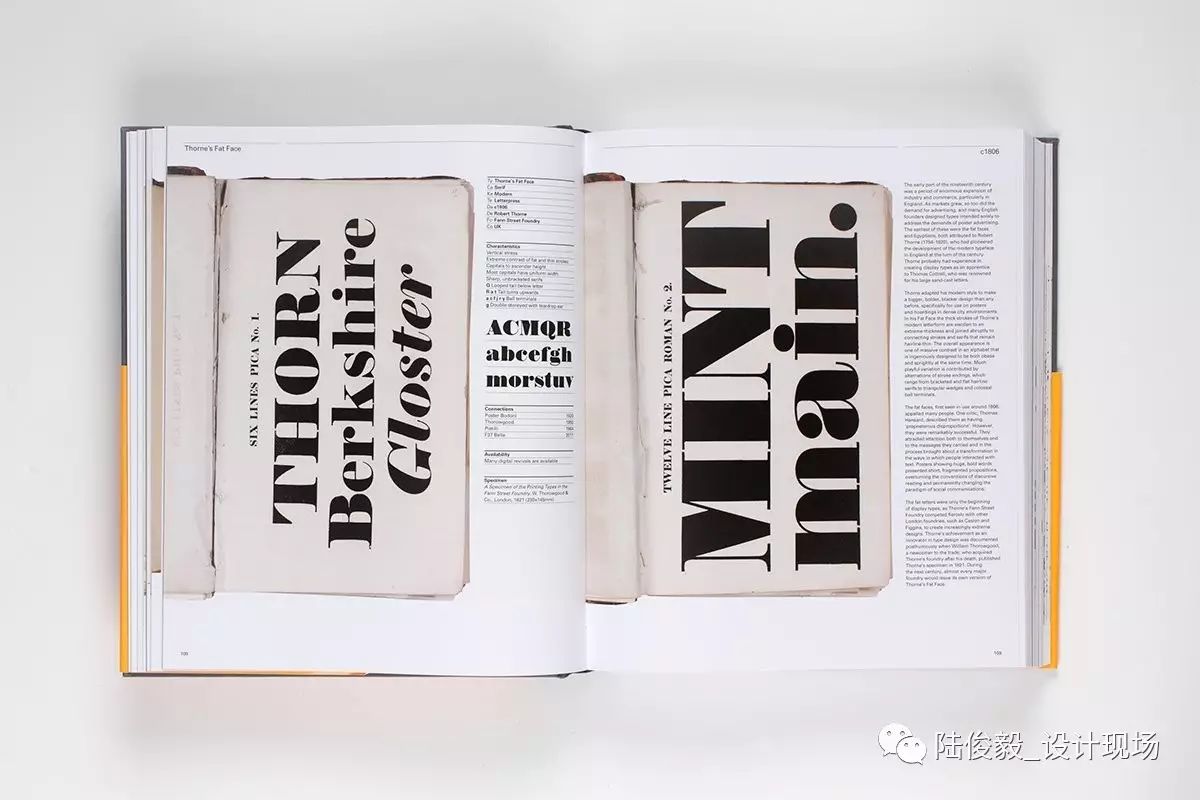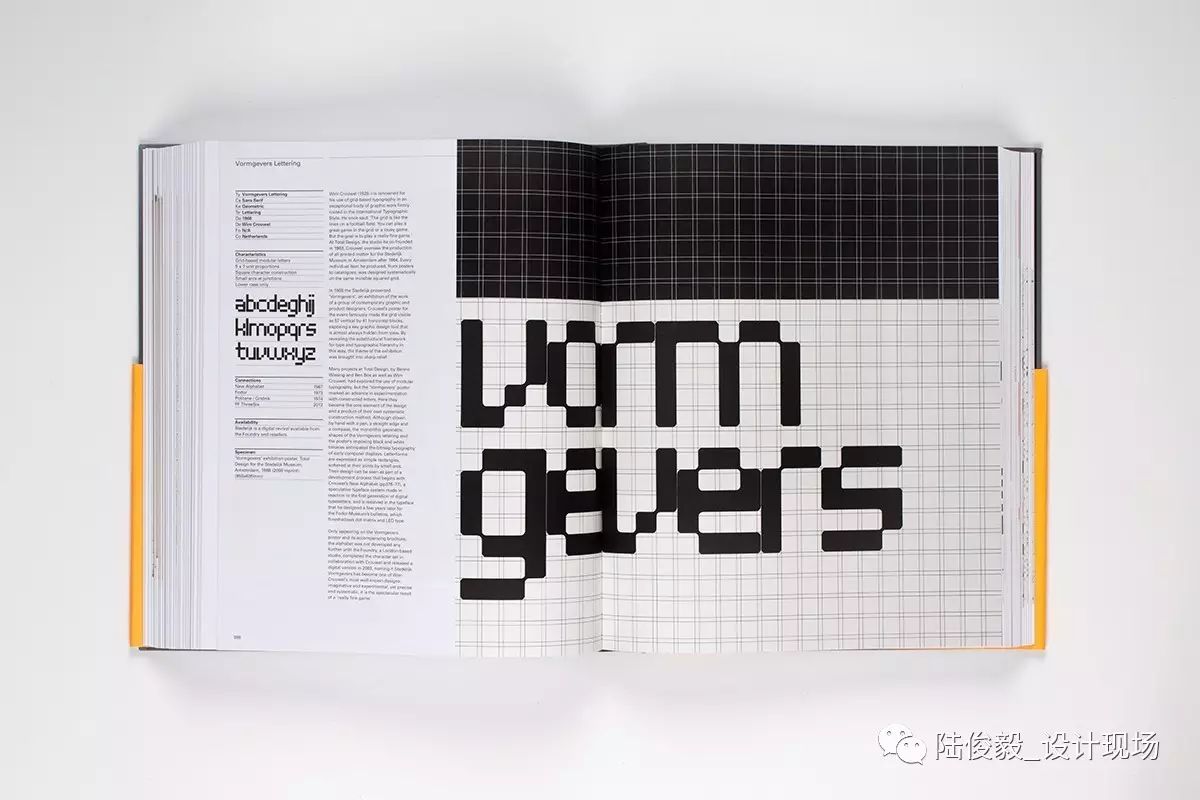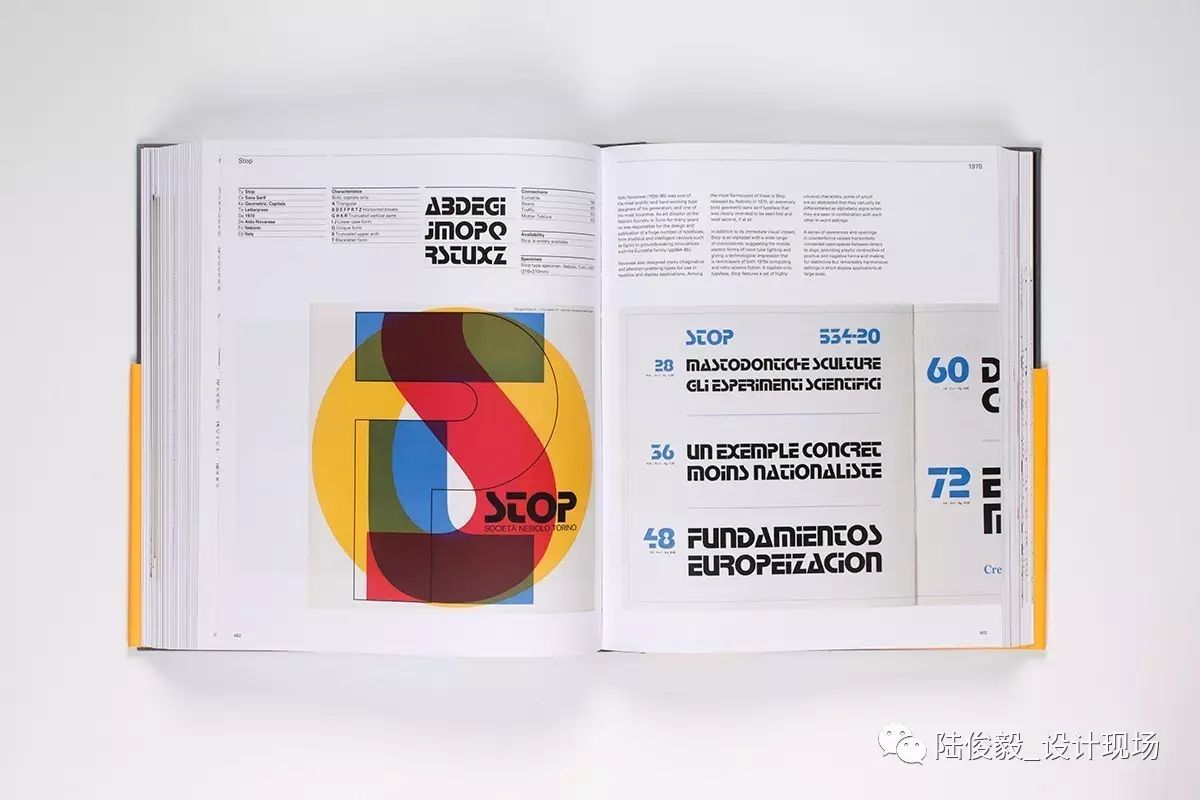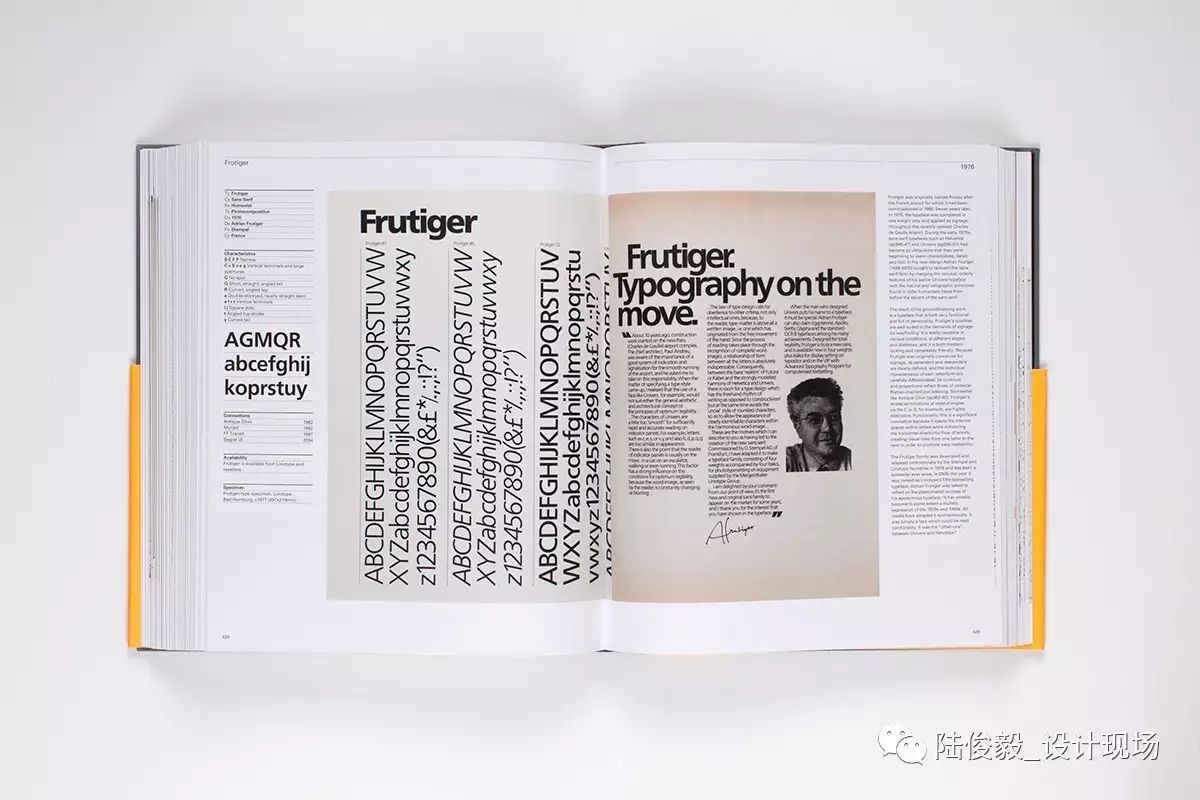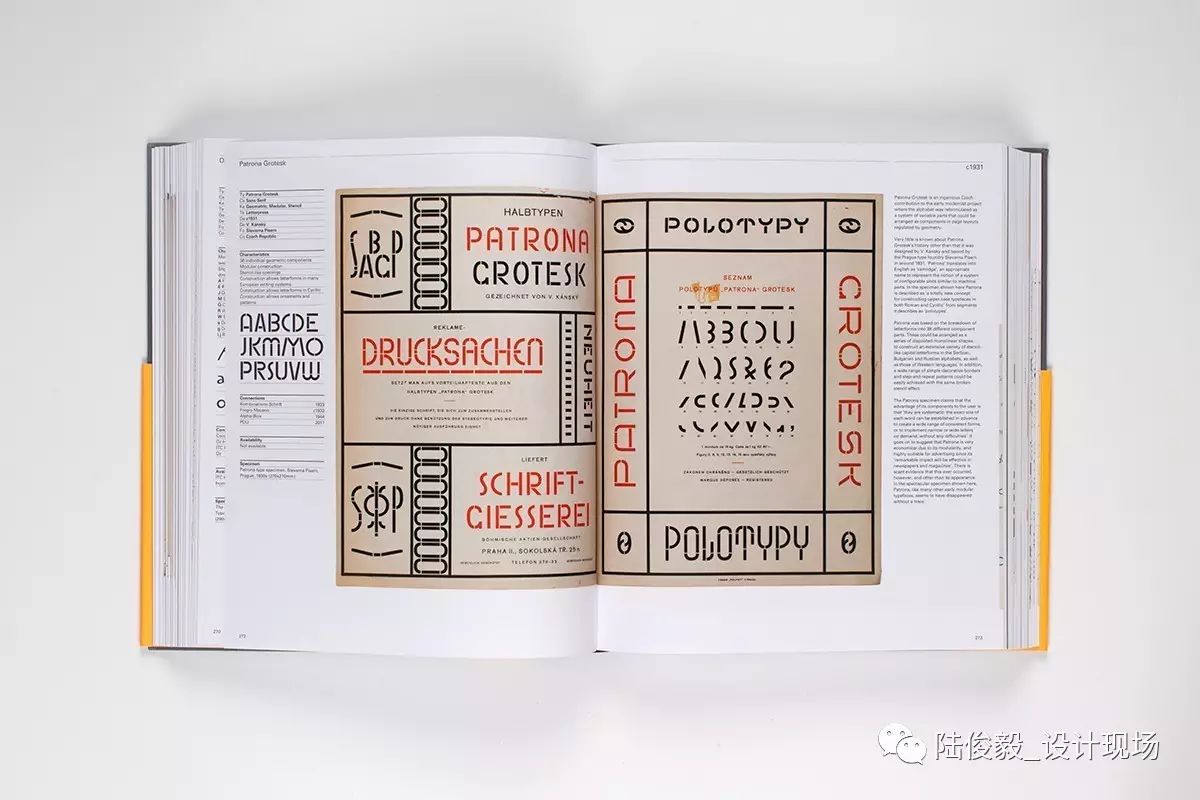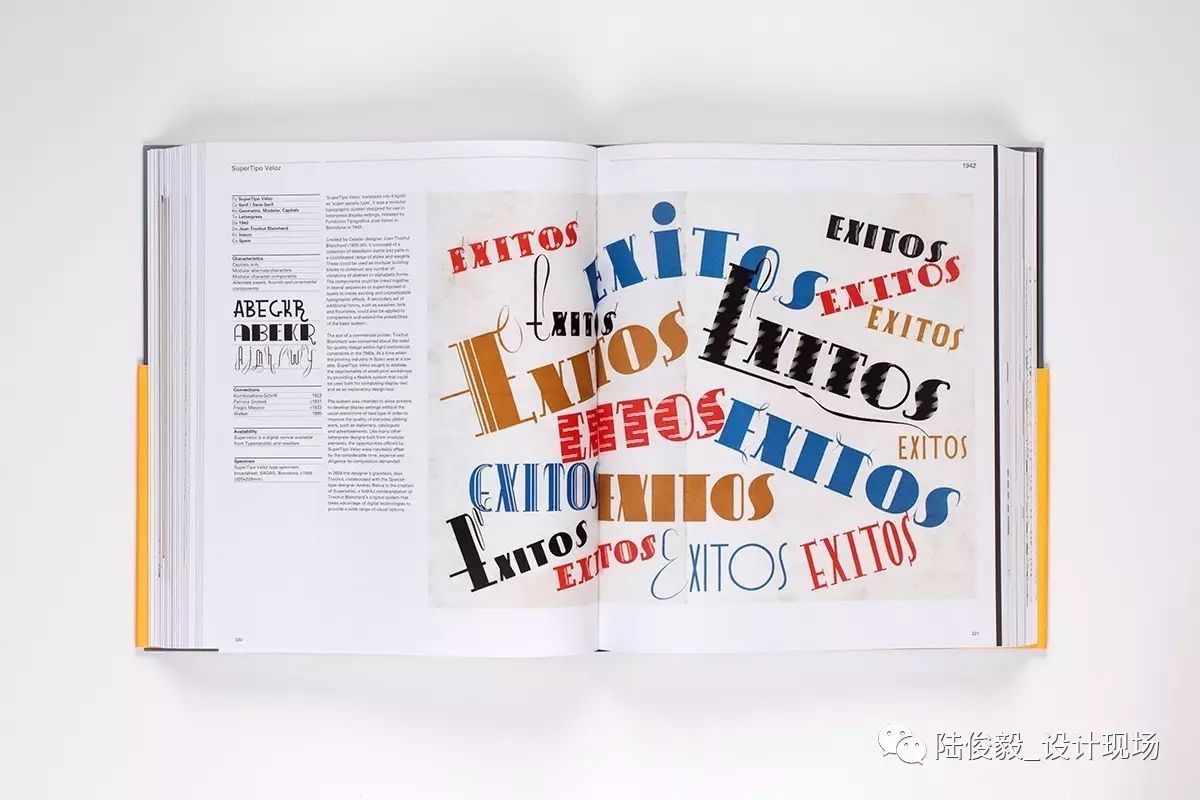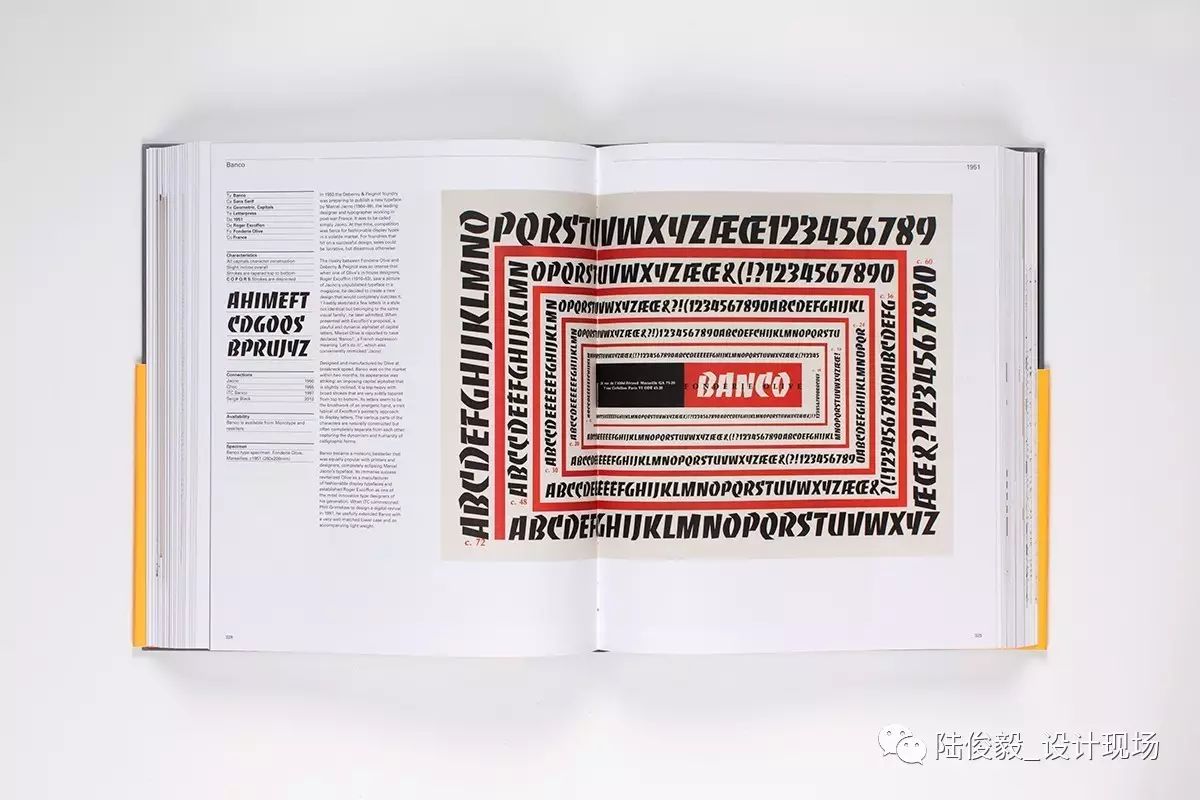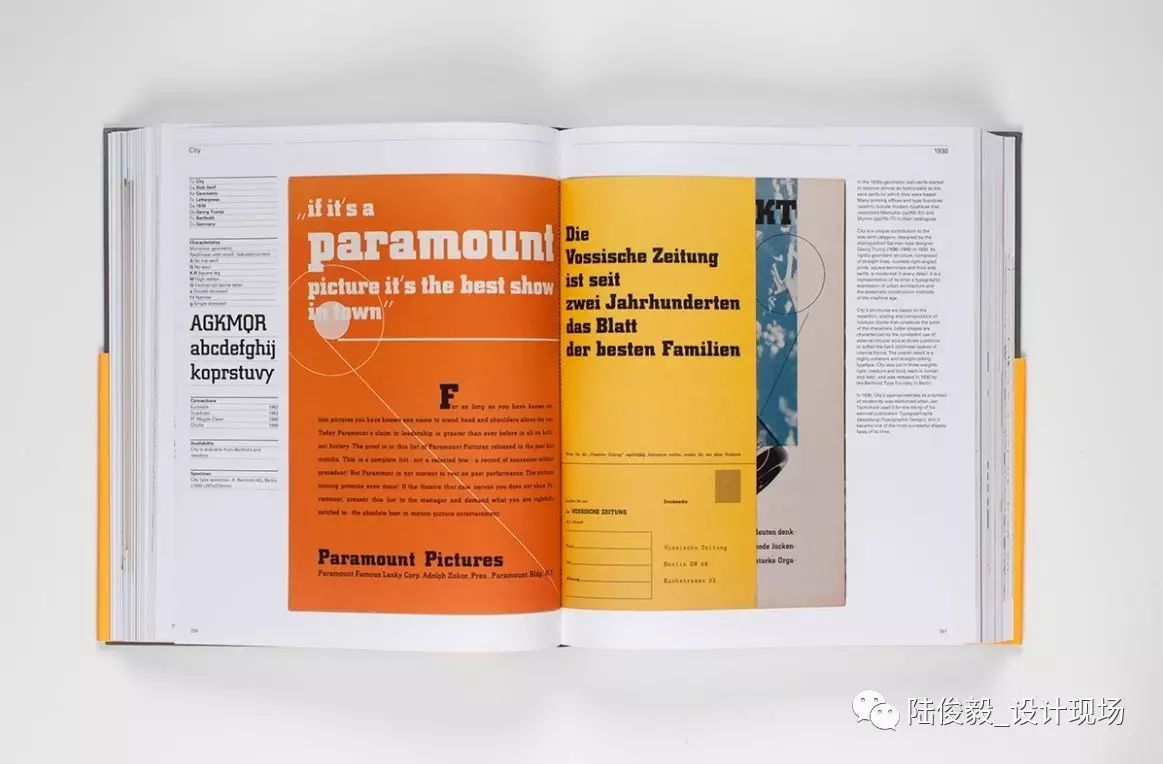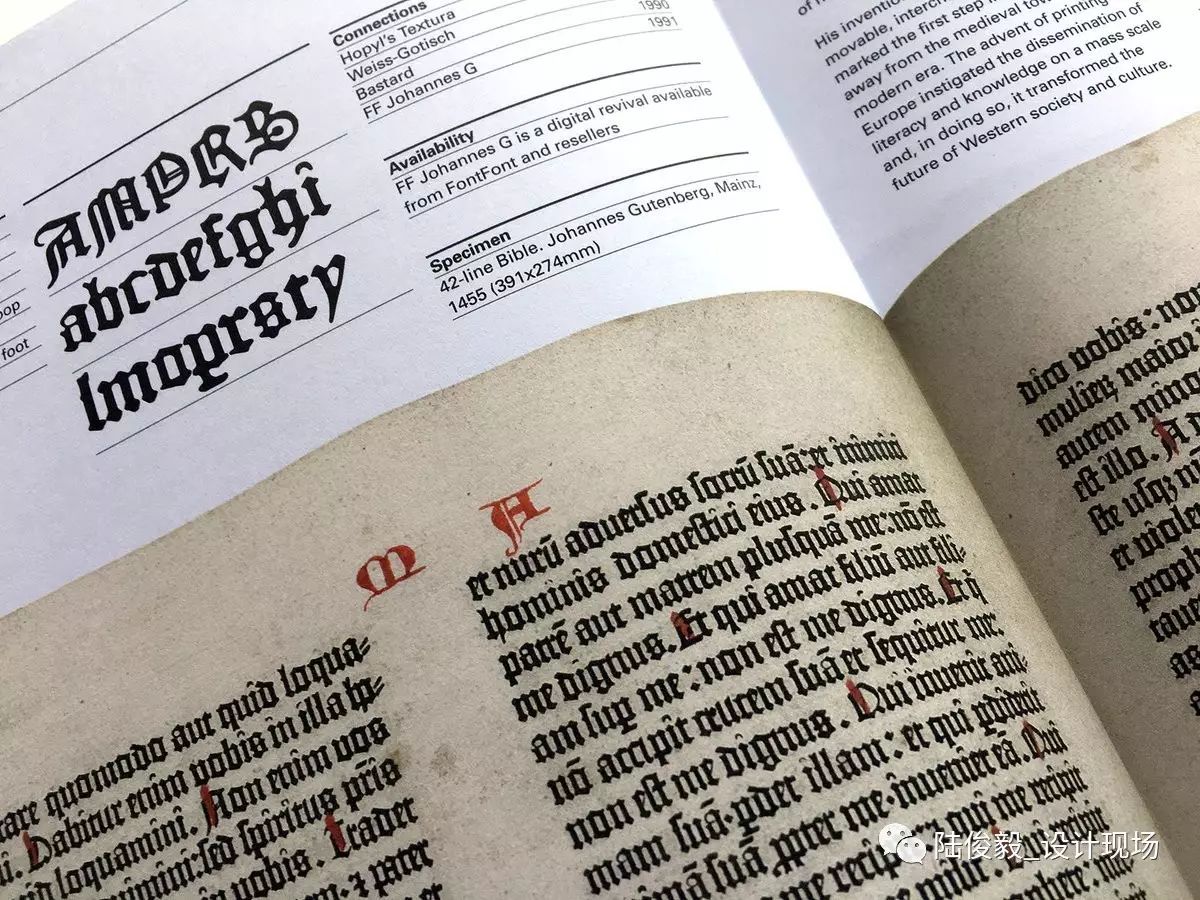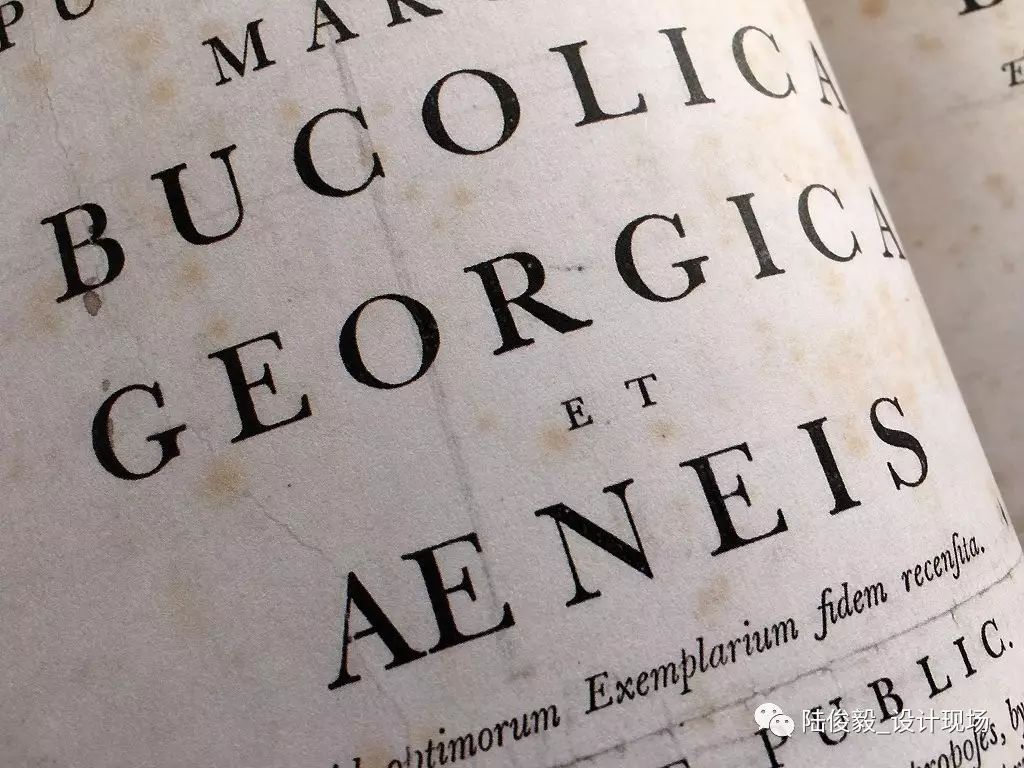
设计案书籍分享:字型的视觉史
作为书和字型的爱好者,在书桌上出现一件两者的混合物,而且还是重量级的一件,简直就是盛宴!
由 MuirMcNeil 工作室的 Paul McNeil 编写,Laurence King 出版的《字型的视觉史(The Visual History of Type)》就是这样一场盛宴,我也很荣幸把这本书分享给你们。比起简单的再版印刷,这本包含350张插图的672页的精装书的发行可能具有更大的价值。在这本书本月正式发行之前,我们与它的作者 Paul 进行了一场对话,以便让大家深入的了解这本书编辑和设计过程中的来龙去脉。
Paul McNeil
可以和大家介绍一下您的背景吗?
2001年重新回到伦敦印刷学院(London College of Printing)读取文字研究的硕士学位之前,我已经作为平面设计顾问的角色工作了三十多年。我过往的设计实践主要集中为科技与传播领域的商业应用和非政府组织进行品牌与企业视觉识别的设计工作,但近些年来我逐渐减少了商业工作,转而更多的从事设计教育。在2010至2016年期间,我在伦敦传媒学院(LondonCollege of Communication)教授研究生课程并且也担任文字研究硕士课程的负责人。我和 Hamish Muir 在2010年共同成立了新的工作室MuirMcNeil以进行一系列综合的设计委托和独立设计项目,在这里我们进行的所有实践都是用基于系统(systems)的方法探索解决视觉传达问题的途径。
为什么要做这本书?又为什么选择在这个时间和这个形式?
我对字型与文字设计这个处于传播交流中心的领域一直怀有浓厚的兴趣,我也在自己的整个职业生涯中一直不断的学习和研究,积累了大量的书籍和设计过程中的样本等相关资料。对我来说,文字设计远不仅仅是一种设计元素和设计工具那么简单。几年之前,我发现除了Jespert、Berry和Johnson编写的具有深远影响的《字型百科全书(Encyclopediaof Typefaces)》和Sutton与Bartram编写的《字型图录(Atlasof Typeforms)》分别从1953年和1968年起不断被再版与重印之外,似乎就再也找不到其它的能够明晰讲述字型历史的著作。此外,在和自己的学生们日复一日的相处和工作中,我也不断的觉察到他们相比之下对于字型历史脉络理解的匮乏。所以,我也想要用这本书填补这块空白,不仅是为了让它能够成为有用的工具书,去帮助设计师理解字型的工作方式和设计的种种原因,也是为了梳理这些字型历史中包含的对技术的丰富连接、与不同时代美学的关联、以及对于社会和思想演变反映等。可以说字型就是人类文化的一种的微观流露的代表。
MuirMcNeil 工作室
显然很多人会觉得这本书的结构应该是按照字型类别划分成 Old Style、Neo Grotesque、Display 和 Didone 等章节,但在我对这本书早期的研究和计划中,我发现这样的定义会带给人们一种完全错误的印象。传统的对于字型的定义方式缺乏连贯性,尤其用一种粗暴的方式按照历史时期、地理位置或者其它主观感受分类,这也给人们造成一种错觉,好像所有东西都可以在这种范畴下被定位,也可以一直这么做下去。这么做也把那些无法被划分在单一的标签之下的字型排除在外,尤其是在数字化字型设计开始以来,这种现象变得更多。
虽然我在自己的职业生涯中创造了大量的印刷物设计,但我也同时积极的避免自己用传统设计修辞方法做设计。在很多书籍中,你会发现版式和文字设计做足了对读者目光的吸引,似乎想要用这种方式弥补内容的不足,用设计教育家Ian Noble的话来说也可以叫“把愚蠢的东西变得漂亮(make a stupid thing lookpretty)”。然而,在《字型的视觉史》这本书中所使用的处理方法恰恰与上述的相反,目的在于我想要为读者提供一份明确且权威的考察文件,呈现从印刷刚诞生的15世纪50年代直到今天为止被设计和生产出的所有重要的字型,并通过一份当代的文件样式着重强调这些历史字型样本最真实的原貌。此外,庞杂的内容让这本书的最终呈现变得非常厚,也出于想要尽可能按照原始尺寸呈现图片,让书的开本也比较大。书中收录的超过320个的字型通过有效的组织全部都用跨页的方式呈现,而且均分别配有对其设计发展、表现和应用的简洁的文字说明,以及固定的相关信息检索表格。
这本书具体是如何被设计完成的呢?是否可以向我们介绍一下这个项目的规模、耗时、故事,以及过程中的决定等等?
总的来说,这本书从最开始的想法到最后的实现跨了7年半的时间,伴随着我的教学和其它各种实践工作,当然,这期间也包括因为种种原因的停滞时间。整个项目可以被划分为最初提案并与Laurence King商讨花费的1年、在选题和图片收集与研究上花费的3年、用于写作的2年以及最后用于对书编辑设计的1年。整个过程中我发现所有的研究工作都很有意思,书的设计工作是一种计划中的任务,而对于整本书的写作,可以说是最艰难的部分。同时担任作者和设计师这两种身份,让实现这本书的过程中相当一部分时间都是独自一人的努力,甚至可以说有一点孤独,所以我可能更喜欢像从前一样在一个团队中工作。但是这本书的成功离不开下面这几位朋友的支持:整本书图片素材的研究者 Giovanni Forti,用他极大的耐心和毅力收集到远超过我预期的从古登堡学会(Gutenberg’s Textura)到Cassandre 的 Bifur 等一系列的素材资料;协助拍摄所有图像的摄影师 Ida Riveros;在最后阶段加入我们,既勤奋又幽默的编辑 Philip Contos。
对于这个规模的书籍项目来说,它的实现少不了来自很多人的贡献,他们在这个过程中分享自己的专业知识,提供一系列的资料,我尤其要提到对于这本书极其重要的伦敦 St Bride 图书馆。我在那里翻阅惊人的馆藏中的各种历史样本,度过了很多愉快的时光,也要感谢图书管理员 Bob Richardson 提供的帮助。我得说,St Bride 图书馆绝对是个无与伦比的资源宝库,希望它一直好好的留存下去。
尤其对于今天的学生们来说,他们常会通过数字媒介获取各种刺激,甚至当今的设计史和设计教育也都被大量的数字化取代,在这种情况下,您觉得这种开本和价格的实体书扮演着怎样的角色呢?
虽然数字媒介在今天被广泛的使用,但无论是在教育上还是其它方面,我并没有觉得它像你的问题中暗示的那样彻底的取代的印刷媒介。人们常习惯性的去用一种完全相反或完全改变的方式理解事物,比如看见很多人都通过屏幕获取讯息,而后就认为印刷已经完全死去。但我们可以找到很多证据证明新旧媒介能够并存,也将很可能继续这么存在下去。印刷出版曾作为唯一的媒介,已经肩负大众传播的职责相当长的时间,虽然说在一些特定的方面印刷物依然比数字媒介更具互动性、更及时也更个人化,而且与相同内容的数字出版物不同的是印刷物总有一种与投资它成比例的价值存在,也更容易追溯到信息源头,更不像数字内容一样需要花费很多验证真实可靠性的消耗,但这只是关于媒介与相互协调的一些模糊的说法。对于《字型视觉史》这本书来说,印刷出版毫无疑问的是首选媒介,因为它提供了对于内容与形式最直接的关联,正如你看到的书中大量的内容和资料本身就直接与印刷有各种各样的连接。在此,我也要由衷感谢 Laurence King 对于这本书的巨大投资才让它最终呈现在大家眼前。到目前为止,我们还没有计划要制作一份数字版本,但我也并不是捍卫传统媒介的保守者,在 Kindles 和 iBooks 盛行的今天,我们也可能将会把这本书制作成一个网站,并用严谨且高标准的编辑与策划的态度持续扩充资料的数据库。
您是如何决定哪些字型应该被放进书中?哪些又不需要?又有没有哪些你喜欢的最终在书中有遗漏的字型?
因为我在文字设计的领域已经沉浸了相当长的一段时间,以至于我在一开始的时候就已经有了一个清晰的思路,但在编辑的过程中我也有很多有价值的新发现,比如1922年的Bremer Presse Antiqua和2015年Sandrine Nugue发行的Infini。所有这些都被通过表格清晰的罗列出来,在我拜访图书馆馆藏以及从 Laurence King 的图片研究者得到精选后的图片的同时也保持着持续的增补。书中的320多种字型都是经历过时间检验的经典之作,比如一代又一代读者都发现Garamond和Baskerville具有可以被轻松阅读的识别性,印刷商和出版商也一直把这两款字作为高质量文字设计的标准,它们兼具了效率与美学的双重考量。但是,由于这本书的目的在于呈现每个阶段发展的精准图片,因此书中的一些字型可能只拥有幸存下来的的少许简洁的资料说明和展示。此外,书中还收录了一系列极具开创性的实验性的设计,它们可能在商业上均以失败告终,或者从未被发行过,但却都为文字与字型设计领域提供了新方向上的探索。即使这些被收录的实验性的设计中有很多都存在着争议,并且可能会被认为缺少关联、不正确、过于局限、过时,或者被认为是丑陋的代表,但这不妨碍它们被谨慎的挑选下来,以帮助这本书的脉络和叙述更加完整。
可以毫不夸张的说,我觉得字型对人有彻底的吸引力,并且它是人类心灵手巧的产物,对人类文明发挥的影响比任何其它的事物都要大,而且依然在继续。我对书中收录的每一个部分都怀有足够的兴趣(即使是Comic Sans和Arial),我也真诚的希望大家也同样欣赏它们,至少是它们中的大部分。每天我都能够看到新的字型诞生,我也很希望能够把它们收录进书中,比如Bely、Nordvest、Brutal等,但我也很高兴不用去担心我无法改变的事情。
近期还有其它的书或者字型之类的工作计划吗?
我正开始做一个关于书的材料的研究工作,从速记(stenography)到象形文字(pictography)等,以更深入的去了解语言和呈现它的所有可能的可见形式的关系。因为现在刚开始的早期阶段,我也可能在未来完全的转变研究的主题,但我希望能够进展下去。